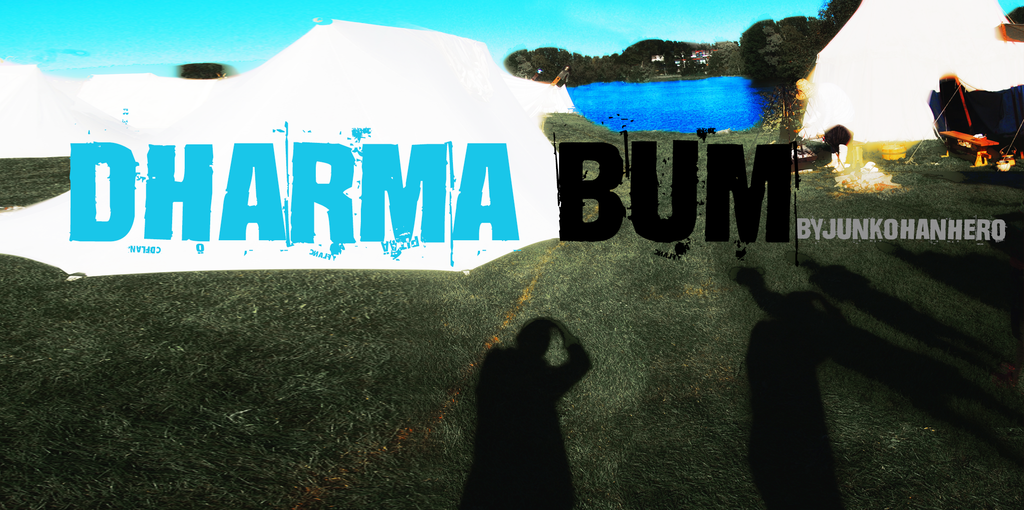
Estamos muito felizes por você escolher a Dharma Bum Font para seu projeto! Esta fonte sem serif é ideal para criar designs modernos e elegantes que se destacam na web e nas aplicações digitais. Desenvolvida pelo designer Hamilton, ela traz uma aparência minimalista e clean, certamente o fará se sentir em casa. Se você deseja utilizar essa fonte em um projeto comercial, é simplesmente necessário adquirir a licença de uso comum. Para isso, basta enviar 15€ ou $20 através do PayPal para mim, eu ficarei feliz em liberar as permissões necessárias ao seu projeto. Além disso, você pode usar nosso botão de doação, que está bem perto da caixa de download, se preferir. Não importa o uso que você deseje dar à Dharma Bum Font, nós na Hamilton estamos aqui para garantir que ela seja usada da maneira mais criativa e eficaz possível. Sempre com muito prazer em ajudar nossos usuários a explorarem as possibilidades desta fonte única.